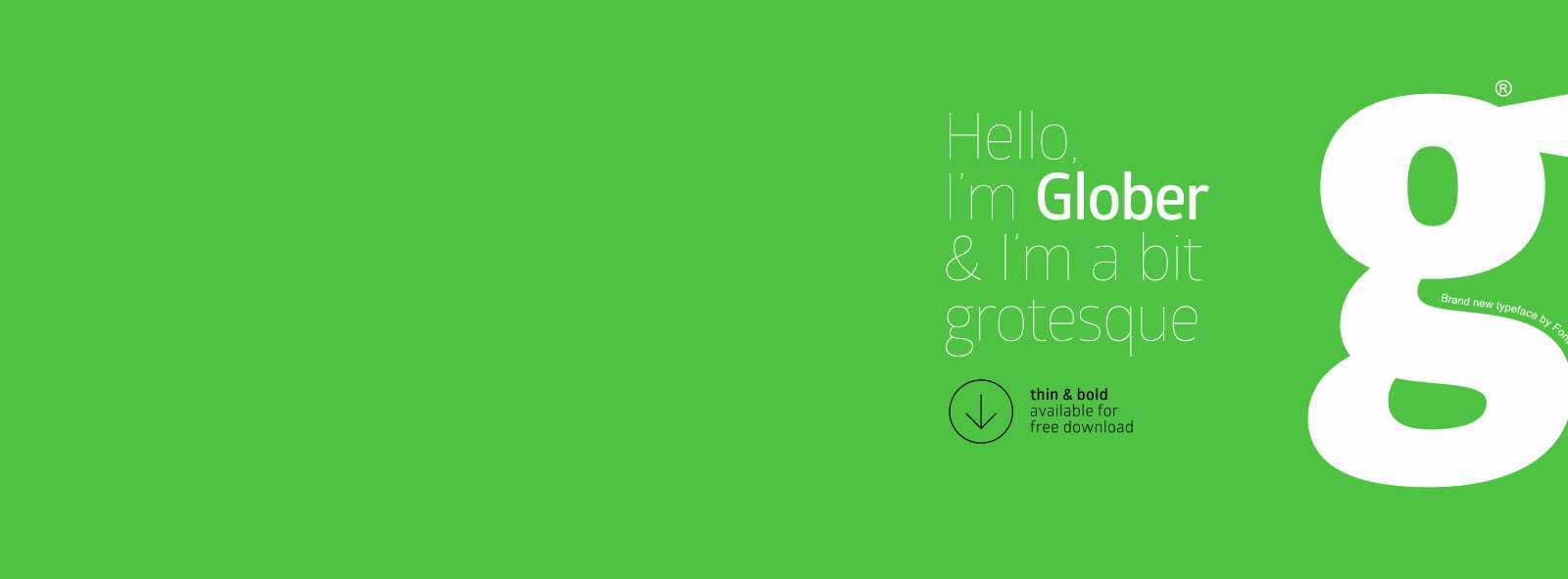
Glober Free Classical Grotesque Font – Download Grátis
Glober é uma fonte inspirada nos tipos grotescos clássicos, com um estilo único que expressa formas geométricas suavizadas de uma maneira perfeitamente perfeita. Este recurso gráfico, com 18 pesos, abrange sete pesos afins e seus respectivos itálicos, oferecendo uma ampla gama de opções que atendem a diversos níveis de tipografia, tanto para headlines quanto para bloquinhos de texto que variam desde o máximo até o mínimo. Com seu formato arredondado, Glober é perfeitamente adaptável a qualquer tipo de design gráfico, seja para web, impressão, gráficos em movimento ou até mesmo aplicado a camisetas e outros itens como posters e logotipos. Este recurso gráfico é uma escolha perfeita para quem busca uma fonte moderna e sofisticada para seus projetos em qualquer formato de mídia.